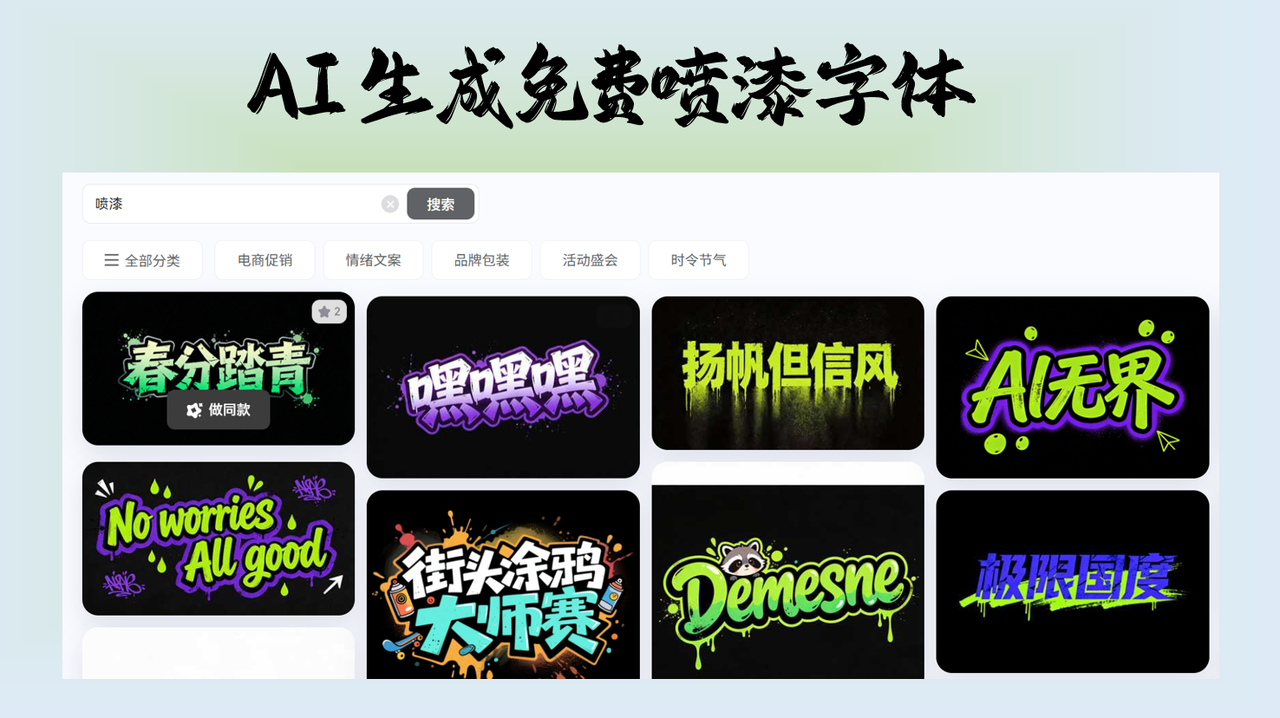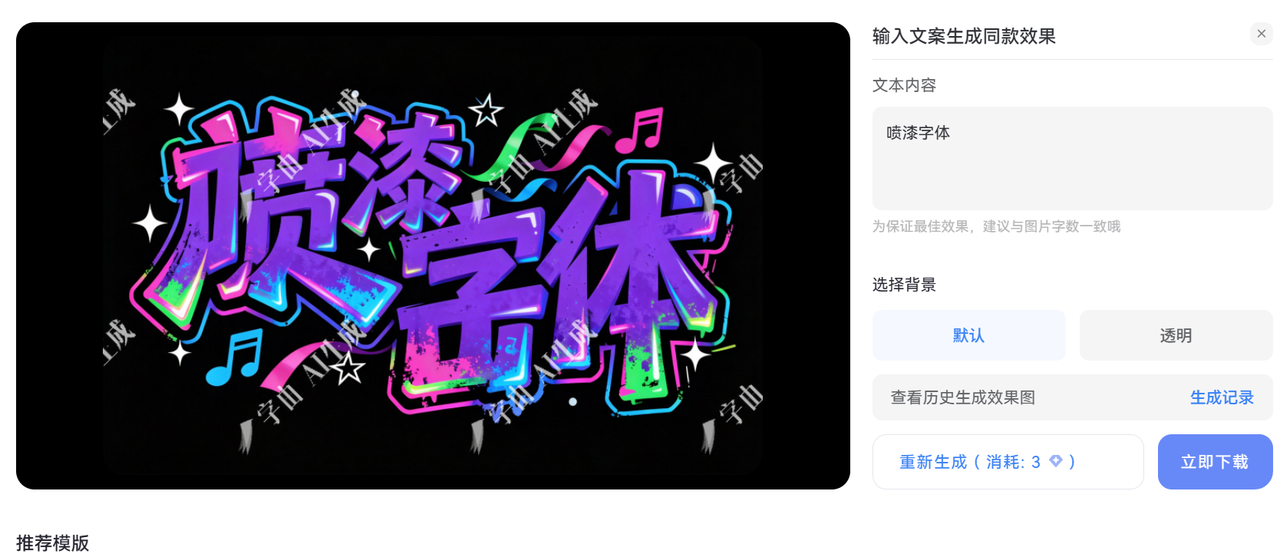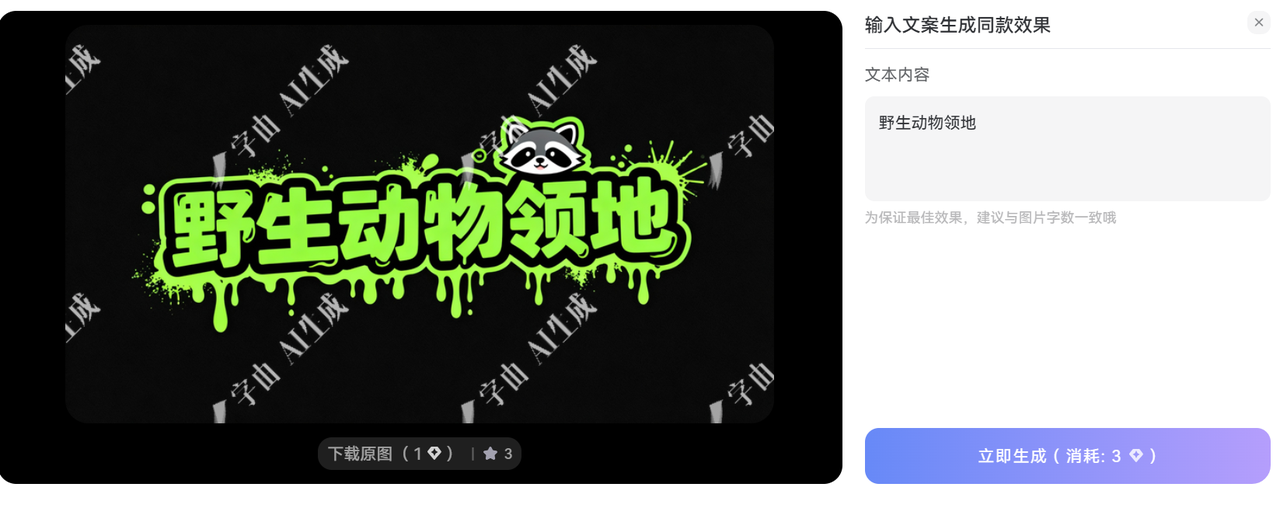
免费商用的喷漆字体下载,来试试让 AI 帮你生成
在设计海报、海报制作、产品包装或活动宣传时,很多人都遇到同一个问题:想要做出那种喷漆效果的文字,却找不到免费且能直接商用的字体。手动在PS里调笔刷画文字又费时费力,买正版字体又要花钱。每天都需要这类艺术字的人,往往不知道从哪里下手。
如果您是新人设计师或者小工作室主,我强烈推荐您先试试这些免费商用的喷漆字体AI辅助生成工具,您可以直接输入文字,就能快速生成各种喷漆风格的字体,然后下载使用。
为什么喷漆字体这么受欢迎?
喷漆字体(也叫喷漆风格字体、连筋喷漆字体)最早起源于街头涂鸦和喷漆艺术。它最大的特点就是文字边缘有明显的笔触、粗细变化和“喷溅”效果,看起来像真的用喷漆笔写出来的。相比普通黑体或圆体,这种字体更有个性,能让您的设计立刻从平庸变出潮流感。
在实际使用中,我发现喷漆字体特别适合以下场景:
- 活动宣传:音乐节、演唱会、展会海报
- 产品营销:服装店招牌、包装盒文字
- 短视频内容:抖音、B站的标题和叠加字幕
- 日常办公:PPT标题更醒目
它不像手写体那么工整,也不像印刷体那么规整,而是带点随意却又专业。免费商用的喷漆字体下载后,您就可以在各种软件里直接套用,不需要额外处理,效果直接呈现。
使用 AI 字体生成喷漆字体
搜索模板
在搜索框中输入“喷漆”,在列表中找到适合自己的喷漆模板
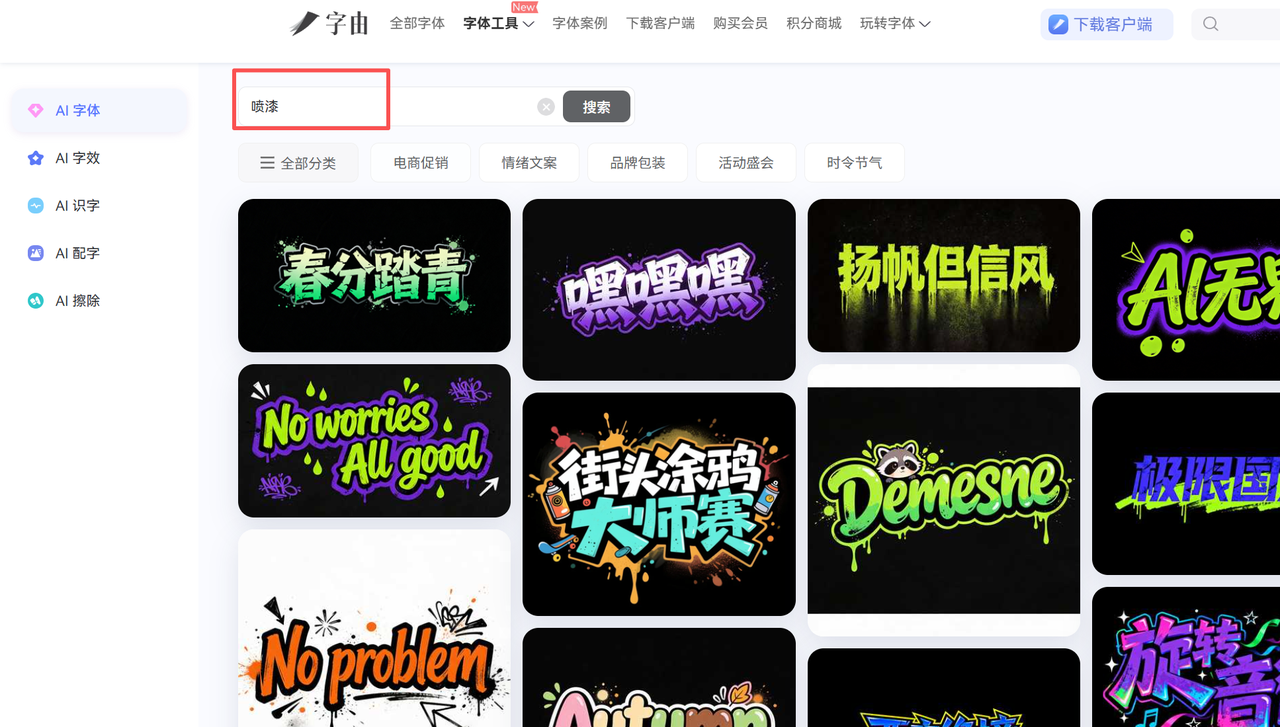
AI 生成
点开具体模板后,输入自己的文案,就可以使用 AI 一键生成相同效果的喷漆字体了。
- 为保证最佳效果,建议与图片字数一致
喷漆字体下载
如果对 AI 生成的结果满意,一键下载透明的结果到本地,在其它设计软件上使用。
我推荐的几个喷漆字体模板
我试用过几个不同风格的免费商用的喷漆字体模板,如果大家不知道如何选择,可以先试试这几款
野生动作领地
有点可爱的喷漆字体
街头涂鸦大师赛
非常潮流的一款,适合嘻哈、街舞等场景
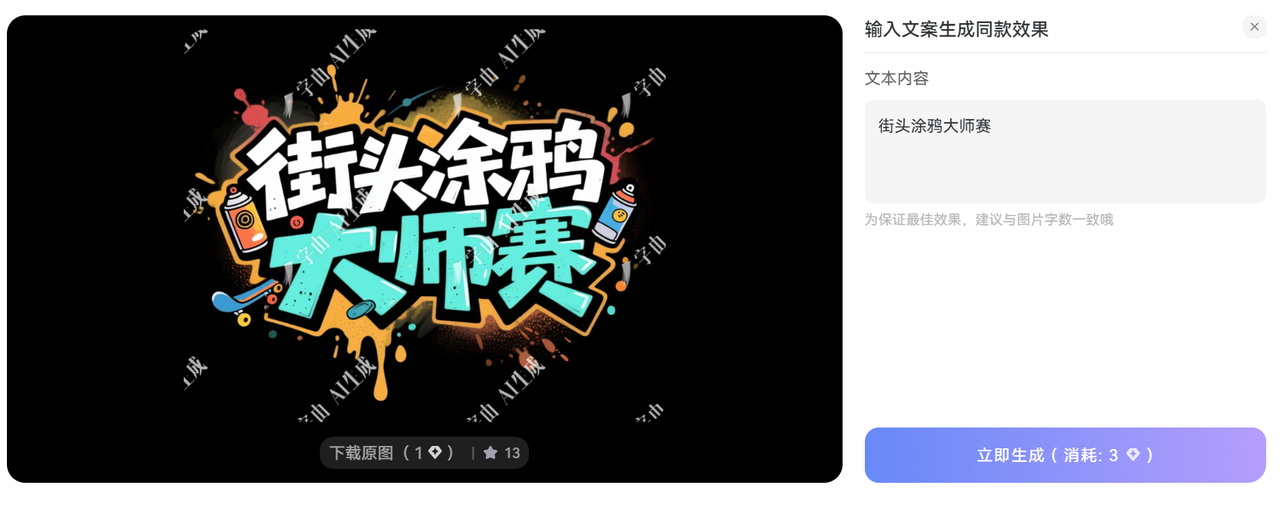
西之绝境
非常酷的一款喷漆字体,游戏行业可以先尝试这款
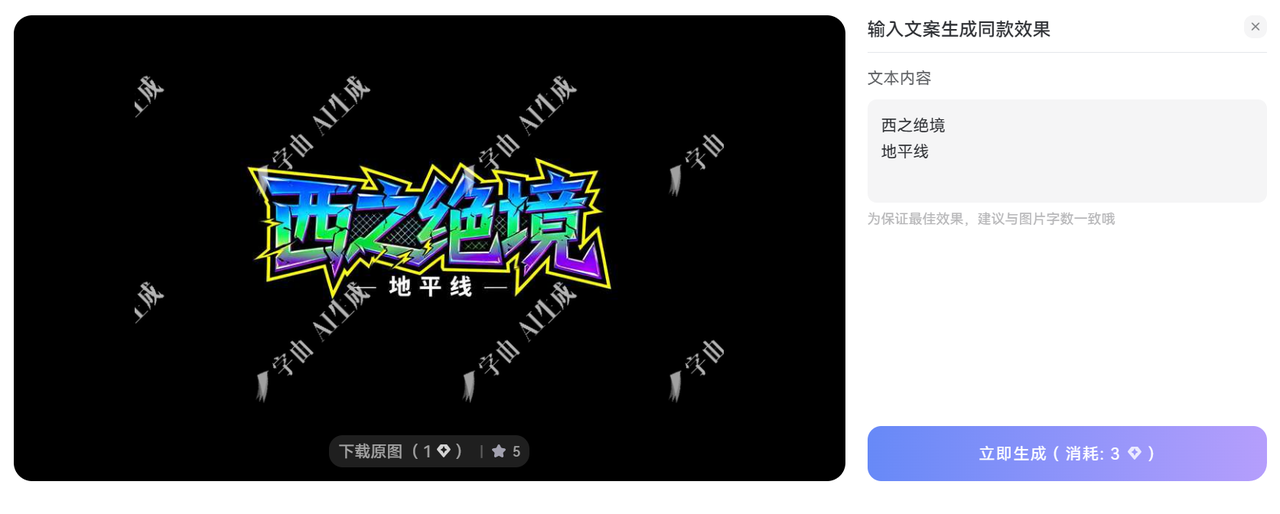
喷漆字体不是一种新鲜事,而是设计师工具箱里一直存在的实用选择。免费商用的喷漆字体下载让每个人都能拥有高质量艺术字,省钱省时还能提升设计质感。